싸인은 단순한 서명이 아니라 본인의 브랜드를 나타내는 중요한 요소예요. 특히 글씨체를 어떻게 선택하느냐에 따라 싸인의 분위기와 인상이 완전히 달라질 수 있어요. ✍🔥
내가 생각했을 때, 프로페셔널한 싸인을 만들려면 가독성이 좋으면서도 개성이 살아 있는 글씨체를 선택하는 것이 중요해요. 이제 싸인에 적합한 다양한 글씨체를 살펴볼까요? 🚀
프로페셔널한 싸인의 중요성 🏆
싸인은 단순한 글씨가 아니라 본인의 정체성을 드러내는 중요한 요소예요. 특히 비즈니스나 공식 문서에서 사용될 경우, 싸인의 스타일이 신뢰도와 인상을 좌우할 수 있어요. ✍🔥
🔹 프로페셔널한 싸인이 중요한 이유
✔ 공식 문서에서 신뢰감을 줄 수 있음
✔ 비즈니스 서명에서 강한 인상을 남길 수 있음
✔ 고유한 싸인은 브랜드처럼 기억되기 쉬움
✔ 서류, 계약서, 명함 등에 사용할 때 가독성이 중요함
📌 프로페셔널한 싸인의 핵심 요소 ✨
요소 설명 가독성 읽기 쉬운 글씨체 선택이 중요 일관성 싸인을 할 때마다 동일한 스타일 유지 스타일 곡선과 직선을 활용해 개성 있는 디자인 연출 간결함 복잡하지 않으면서도 빠르게 쓸 수 있어야 함 이제 싸인에 적합한 글씨체 종류를 살펴볼까요? ✍
싸인에 적합한 글씨체 종류 ✍
싸인에 사용할 글씨체는 스타일, 가독성, 개성을 고려해 선택해야 해요. 특히 공식 문서에 사용할 싸인이라면 너무 복잡하지 않고 빠르게 쓸 수 있어야 해요. ✍🔥
🔹 싸인에 적합한 글씨체 종류
✔ 필기체(Signature Fonts) – 자연스럽고 부드러운 흐름
✔ 고딕체(Gothic Fonts) – 단단하고 강렬한 인상
✔ 세리프체(Serif Fonts) – 클래식하고 우아한 느낌
✔ 산세리프체(Sans-serif Fonts) – 깔끔하고 현대적인 스타일
📌 싸인 스타일에 따른 글씨체 추천 ✨
글씨체 종류 특징 추천 대상 필기체 (Signature Fonts) 부드럽고 자연스러운 흐름, 감성적인 스타일 예술가, 크리에이터, 디자이너 고딕체 (Gothic Fonts) 굵고 강렬한 인상, 힘 있는 스타일 CEO, 사업가, 법조인 세리프체 (Serif Fonts) 전통적이고 우아한 느낌 정치인, 교수, 작가 산세리프체 (Sans-serif Fonts) 깔끔하고 현대적인 스타일 IT 종사자, 마케터, 연예인 이제 한글 싸인 vs 영어 싸인 글씨체 비교를 살펴볼까요? 🔠
한글 싸인 vs 영어 싸인 글씨체 비교 🔠
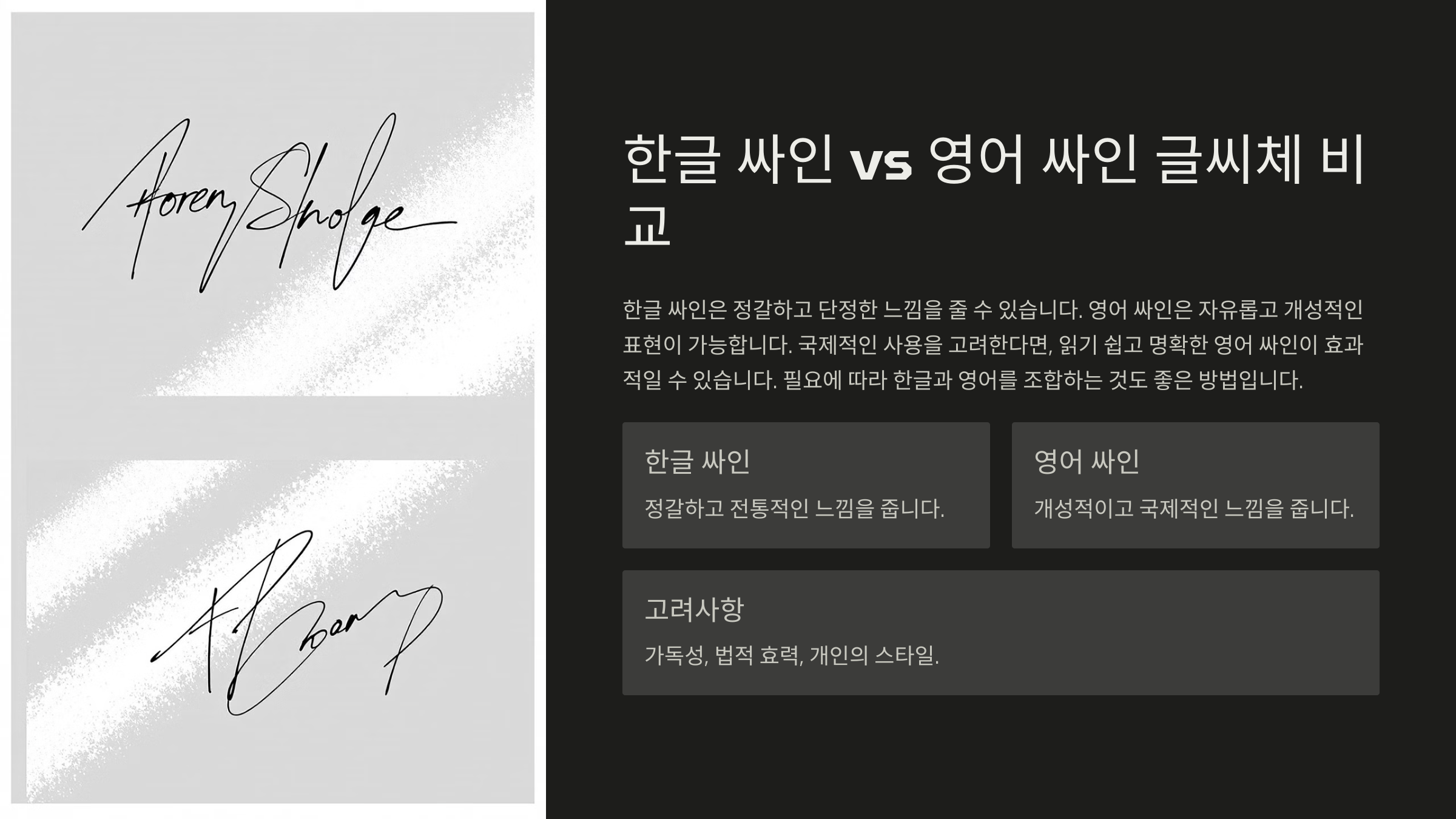
싸인을 만들 때 한글과 영어 중 어떤 글씨체를 선택할지 고민될 때가 있어요. 각각의 글씨체는 다른 분위기와 인상을 줄 수 있기 때문에 용도에 맞춰 선택하는 것이 중요해요! ✍🔥
🔹 한글 싸인 vs 영어 싸인의 차이점
✔ 한글 싸인 – 독창적이고 전통적인 느낌, 개성적인 디자인 가능
✔ 영어 싸인 – 글로벌하고 세련된 느낌, 빠르게 쓰기 용이
✔ 한글+영어 조합 – 한국적이면서도 국제적으로 활용 가능
✔ 필기체 적용 시 한글은 정갈하게, 영어는 자유롭게 디자인 가능
📌 한글 싸인과 영어 싸인의 차이점 ✨
구분 한글 싸인 영어 싸인 느낌 독창적이고 개성 있는 스타일 글로벌하고 세련된 느낌 가독성 획이 많아 복잡해질 수 있음 심플하고 직관적인 형태 속도 쓰기 속도가 비교적 느릴 수 있음 빠르게 쓸 수 있는 디자인 가능 추천 대상 전통적 감성을 원하거나 한국적 이미지를 강조하고 싶은 사람 국제적 이미지가 필요한 사람, 간결한 싸인을 원하는 사람 이제 깔끔하고 세련된 싸인을 위한 글씨체 추천을 살펴볼까요? ✅
깔끔하고 세련된 싸인을 위한 글씨체 추천 ✅
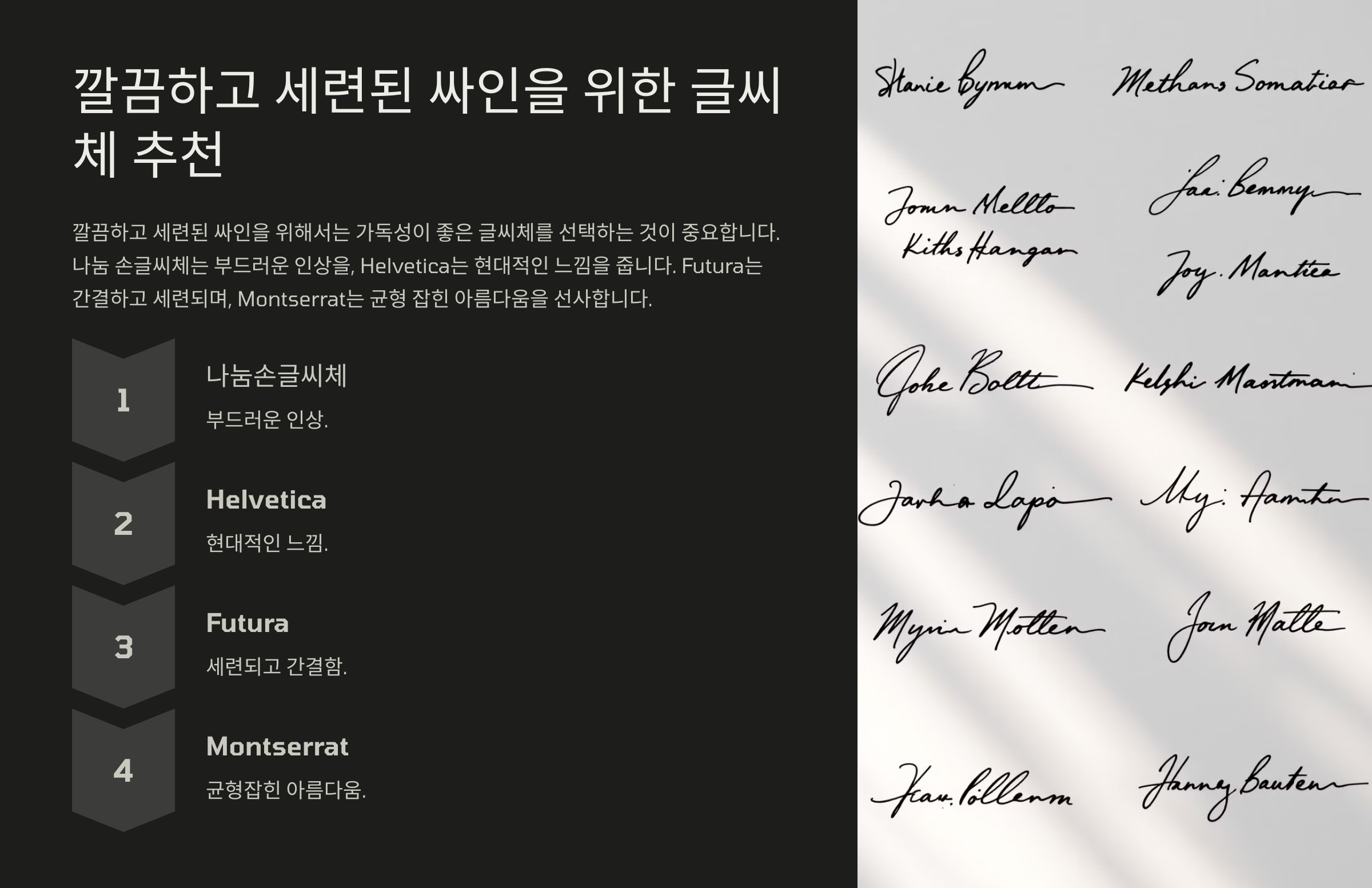
싸인을 깔끔하고 세련되게 만들려면 너무 복잡하지 않으면서도 개성이 있는 글씨체를 선택해야 해요. 특히 비즈니스 문서나 계약서에 사용할 싸인이라면 가독성과 속도를 고려하는 것이 중요해요. ✍🔥
🔹 깔끔한 싸인을 위한 글씨체 추천
✔ Montserrat – 심플하면서도 고급스러운 느낌
✔ Lobster – 필기체 스타일로 자연스러운 흐름
✔ Nanum Gothic – 한글 싸인에 적합한 정돈된 글씨체
✔ Raleway – 얇고 깔끔한 디자인으로 세련된 느낌
📌 깔끔한 싸인을 위한 글씨체 ✨
글씨체 특징 추천 대상 Montserrat 깔끔하고 모던한 느낌, 가독성이 뛰어남 비즈니스, 계약서 서명 Lobster 부드러운 필기체 스타일, 자연스러운 흐름 예술가, 디자이너 Nanum Gothic 한글 싸인에 적합한 정돈된 스타일 한글 싸인 선호자, 공문서 서명 Raleway 얇고 세련된 디자인, 우아한 느낌 브랜드화된 싸인, 명품 스타일 이제 강렬한 인상을 주는 싸인 글씨체 추천을 살펴볼까요? 🔥
강렬한 인상을 주는 싸인 글씨체 추천 🔥
싸인을 통해 강렬한 존재감을 남기고 싶다면, 획이 강하고 독특한 글씨체를 선택하는 것이 좋아요. 특히 사업가, 연예인, 예술가 등 자신만의 브랜드를 구축하는 사람들에게 적합한 스타일이에요. ✍🔥
🔹 강렬한 싸인을 위한 글씨체 추천
✔ Blackletter – 중세 서양 필기체 스타일로 강한 개성 표현
✔ Pacifico – 유려한 곡선과 감각적인 스타일
✔ Oswald – 힘 있고 선명한 직선 형태
✔ Bebas Neue – 강렬하면서도 심플한 인상
📌 강렬한 싸인을 위한 글씨체 ✨
글씨체 특징 추천 대상 Blackletter 고풍스럽고 강렬한 느낌, 중세 유럽 스타일 아티스트, 고유 브랜드 구축 희망자 Pacifico 부드러우면서도 감각적인 곡선 필기체 디자이너, 크리에이터 Oswald 굵고 강렬한 인상, 직선적인 구조 사업가, CEO, 강한 이미지 연출 필요 Bebas Neue 깔끔하지만 강한 존재감, 세련된 직선 디자인 마케터, 연예인, 퍼스널 브랜드 구축자 이제 디지털 싸인에 적합한 글씨체를 알아볼까요? 🎨
디지털 싸인에 적합한 글씨체 🎨
디지털 문서에서 싸인을 사용할 때는 선명하고 일관된 스타일이 중요해요. 특히 태블릿, 전자 서명 프로그램, 그래픽 툴에서 활용하기 좋은 글씨체를 선택하면 더 깔끔한 싸인을 만들 수 있어요! ✍🔥
🔹 디지털 싸인에 적합한 글씨체 추천
✔ Dancing Script – 자연스러운 필기체 스타일
✔ Roboto – 깔끔하고 가독성이 뛰어난 폰트
✔ Signatura – 디지털 서명에 최적화된 세련된 필기체
✔ Futura – 현대적이고 직관적인 스타일
📌 디지털 싸인을 위한 글씨체 ✨
글씨체 특징 추천 대상 Dancing Script 흘려 쓴 필기체로 자연스럽고 우아한 느낌 예술가, 크리에이터, 디지털 서명 Roboto 가독성이 뛰어나고 현대적인 스타일 비즈니스 문서, 공공기관 서명 Signatura 우아하고 세련된 디지털 필기체 브랜드 로고, 전자 서명 Futura 직선적이고 깔끔한 느낌의 현대적 스타일 디지털 계약서, 디자인 관련 서명 이제 싸인과 관련된 궁금증을 해결할 시간! FAQ에서 자주 묻는 질문을 살펴볼까요? ❓
FAQ ❓
Q1. 싸인을 만들 때 가장 중요한 요소는 무엇인가요?
A1. 싸인을 만들 때 중요한 요소는 가독성, 개성, 일관성이에요. ✔ 한눈에 알아볼 수 있도록 명확한 디자인 ✔ 자신만의 스타일이 담긴 독창적인 형태 ✔ 공식 문서에서도 동일하게 유지할 수 있는 일관성
Q2. 싸인에 어떤 글씨체를 사용하는 것이 좋을까요?
A2. 싸인의 목적에 따라 적절한 글씨체를 선택해야 해요. ✔ 공식 문서, 계약서 – Montserrat, Roboto (깔끔하고 가독성 높음) ✔ 디지털 서명 – Dancing Script, Signatura (자연스러운 필기체) ✔ 브랜드화된 싸인 – Oswald, Bebas Neue (강렬한 존재감)
Q3. 한글 싸인과 영어 싸인 중 어떤 것이 더 좋을까요?
A3. 싸인의 용도에 따라 선택하면 돼요. ✔ 한글 싸인 – 독창적이고 전통적인 느낌을 강조할 때 ✔ 영어 싸인 – 글로벌하고 세련된 이미지를 원할 때 ✔ 한글+영어 조합 – 국제적인 활용과 개성을 동시에 살리고 싶을 때
Q4. 싸인을 더 세련되게 바꾸는 방법이 있나요?
A4. 싸인을 세련되게 바꾸려면 불필요한 요소를 제거하고 핵심을 강조하는 것이 중요해요. ✔ 획을 간결하게 정리하여 가독성 향상 ✔ 이니셜을 강조해 브랜드화된 느낌 연출 ✔ 곡선과 직선을 적절히 조합해 균형 있는 스타일 만들기
Q5. 싸인을 빠르게 쓰는 연습법이 있나요?
A5. 싸인을 빠르게 쓰려면 반복 연습과 자연스러운 흐름을 익히는 것이 중요해요. ✔ 매일 5~10분씩 연습하며 손에 익히기 ✔ 크기와 속도를 조절하며 다양한 방식으로 써보기 ✔ 이니셜을 활용해 간결하면서도 직관적인 싸인 연습
Q6. 전자 서명을 사용할 때 주의해야 할 점은?
A6. 전자 서명을 할 때는 보안성과 일관성을 유지하는 것이 중요해요. ✔ 태블릿, 스타일러스 펜을 활용해 자연스러운 필기 연습 ✔ PNG 파일로 저장하여 다양한 문서에 삽입 가능하도록 준비 ✔ Adobe Sign, DocuSign 같은 전자 서명 도구 활용
Q7. 싸인 크기는 어느 정도가 적당할까요?
A7. 싸인의 크기는 문서 종류에 따라 조절하는 것이 좋아요. ✔ 공식 문서, 계약서 – 작은 크기로 간결하게 작성 ✔ 팬 사인회, 명판 서명 – 크고 강렬한 스타일로 작성
Q8. 싸인에 기호(⭐, ✔, •)를 추가해도 될까요?
A8. 기호를 활용하면 싸인에 개성을 더할 수 있어요. ✔ 별(⭐), 밑줄(━), 점(•) 등을 추가해 독창적인 스타일 연출 가능 ✔ 너무 많은 장식은 싸인을 복잡하게 만들 수 있으니 적절하게 사용하기
이제 싸인을 위한 글씨체 선택부터 디자인, 연습법까지 완벽하게 배웠어요! 🎯 연습을 통해 자신만의 멋진 싸인을 완성하고, 공식 문서뿐만 아니라 디지털 환경에서도 활용해 보세요! ✍🔥